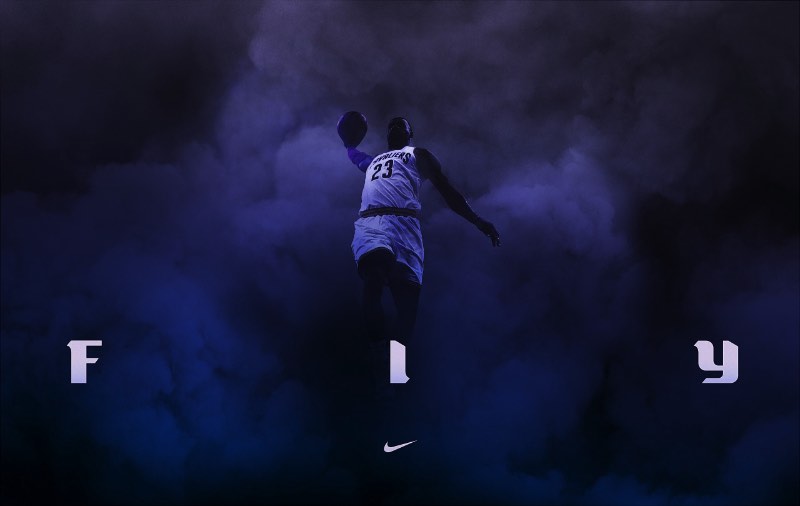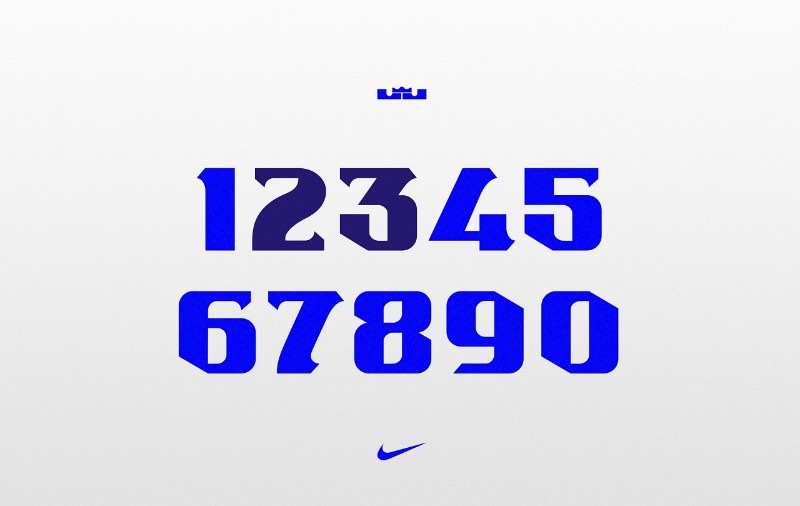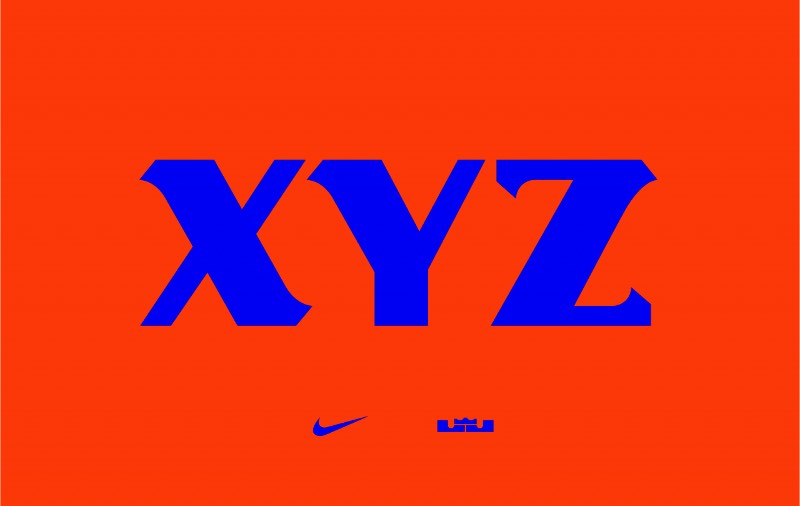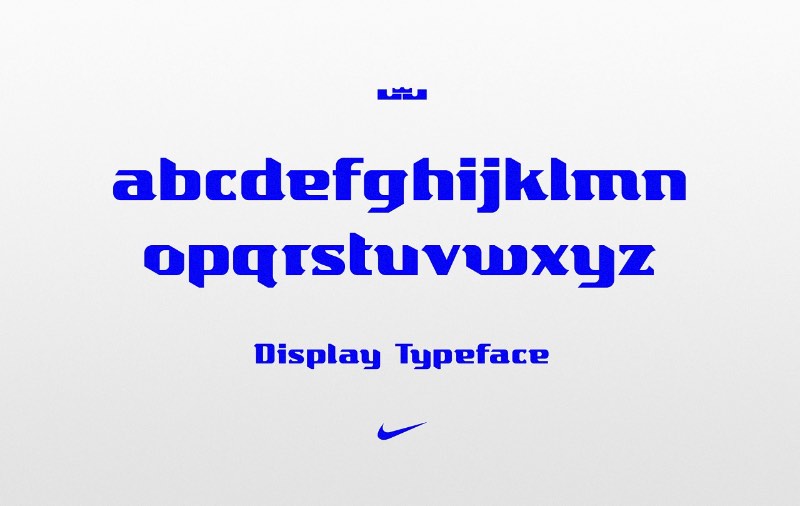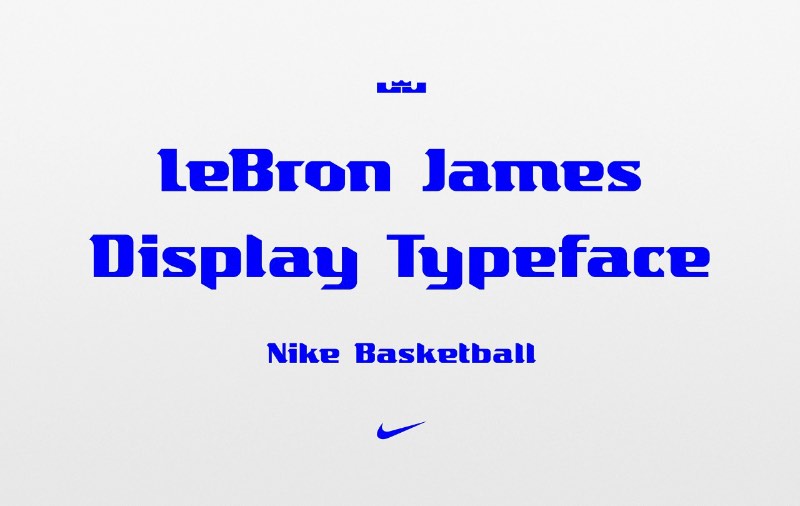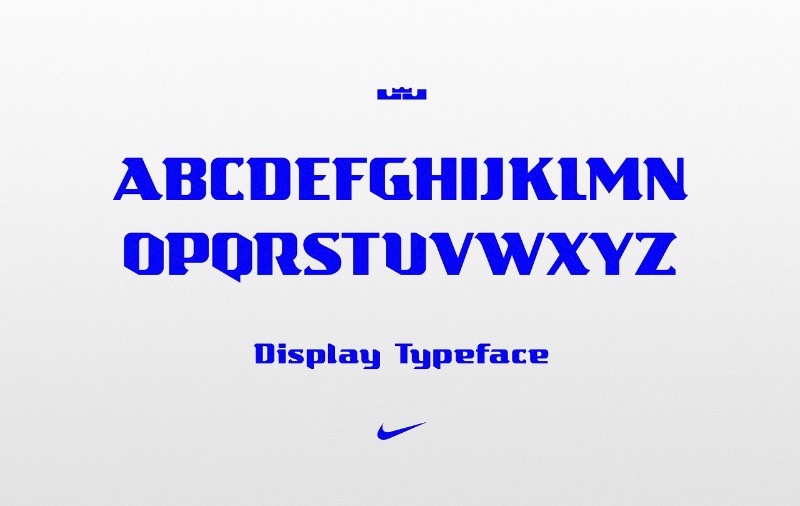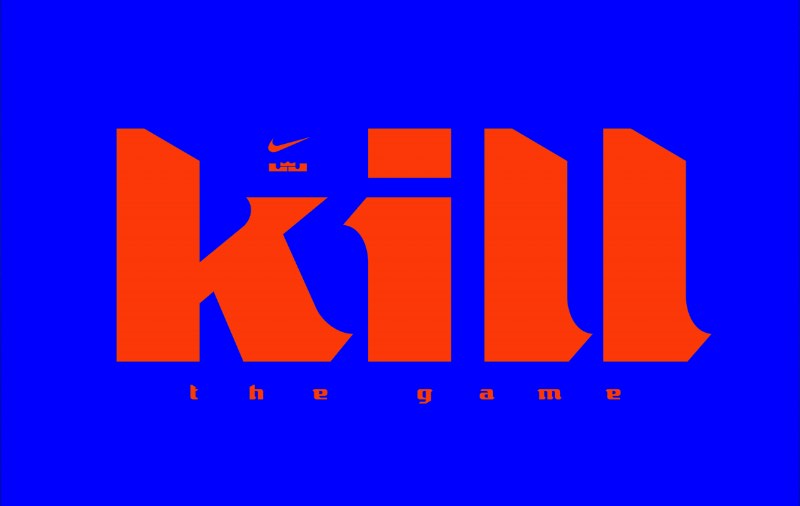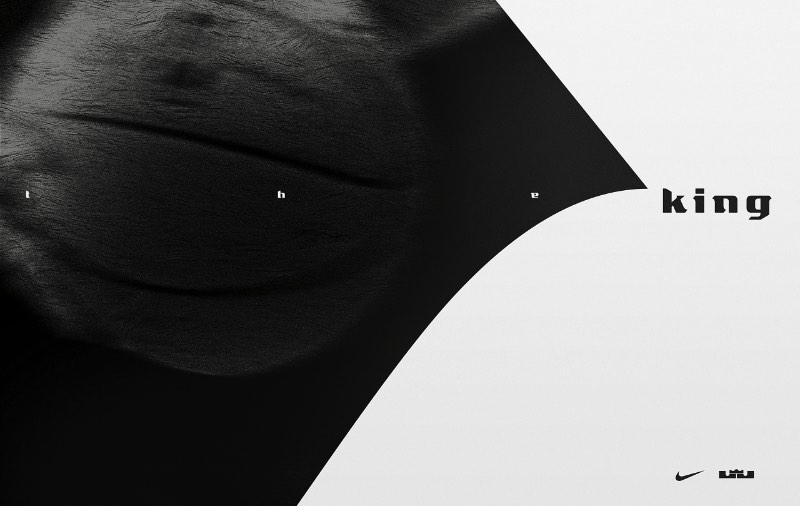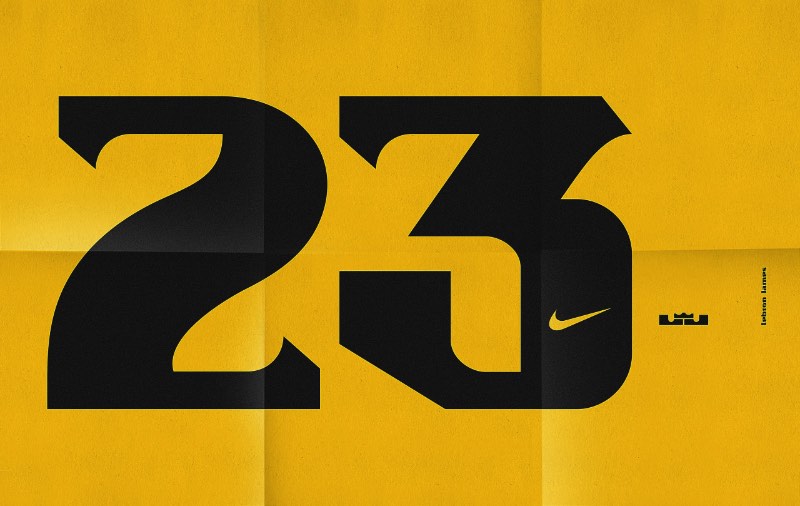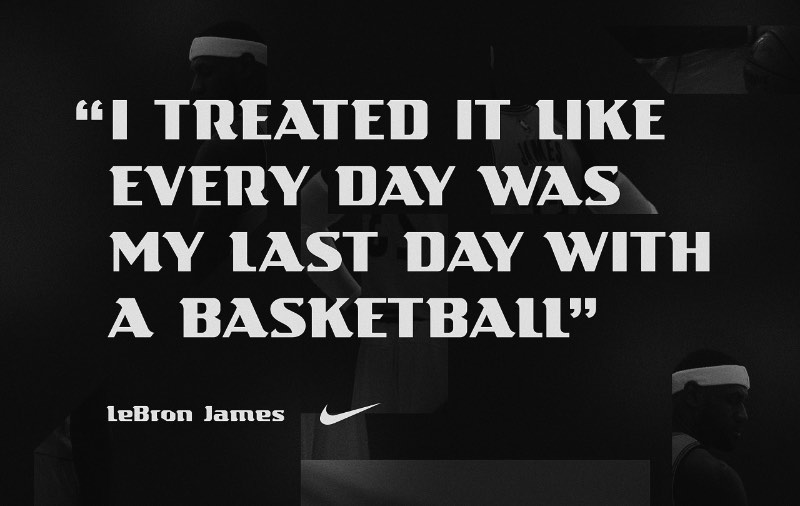
LeBron James e sua tipografia pela Sawdust
No meio de 2015, a Nike anunciou que a Sawdust seria a empresa responsável por criar uma família tipográfica para Kobe Bryant. E, parece que a Sawdust não ficou por ai. Afinal os designers por trás da Sawdust, Jonathan Quainton e Rob Gonzalez, acabaram de lançar uma fonte criada especialmente para LeBron James, uma das maiores estrelas do basquete americano nos dias de hoje.
Essa nova fonte emula muito do dinamismo e energia que você enxerga no trabalho feito para Kobe Bryant mas, as coisas mudam de perspectiva aqui um pouco. O trabalho da Sawdust para LeBron James é mais largo, mais impositor. Acredito que devido ao mais de dois metros de altura do jogador de basquete.
O visual dessa fonte foi inspirado em parte na coroa que o jogador usa como logo, relativo ao título de King James que ele deu a si mesmo. Com traços fortes, quase atléticos e com uma majestade interessante de ver, esse trabalho da Sawdust mostra muito bem a reputação e estatura desse jogador de basquete americano. Veja mais detalhes do projeto logo abaixo.
A Sawdust criou uma tipografia custom para o grande LeBron James